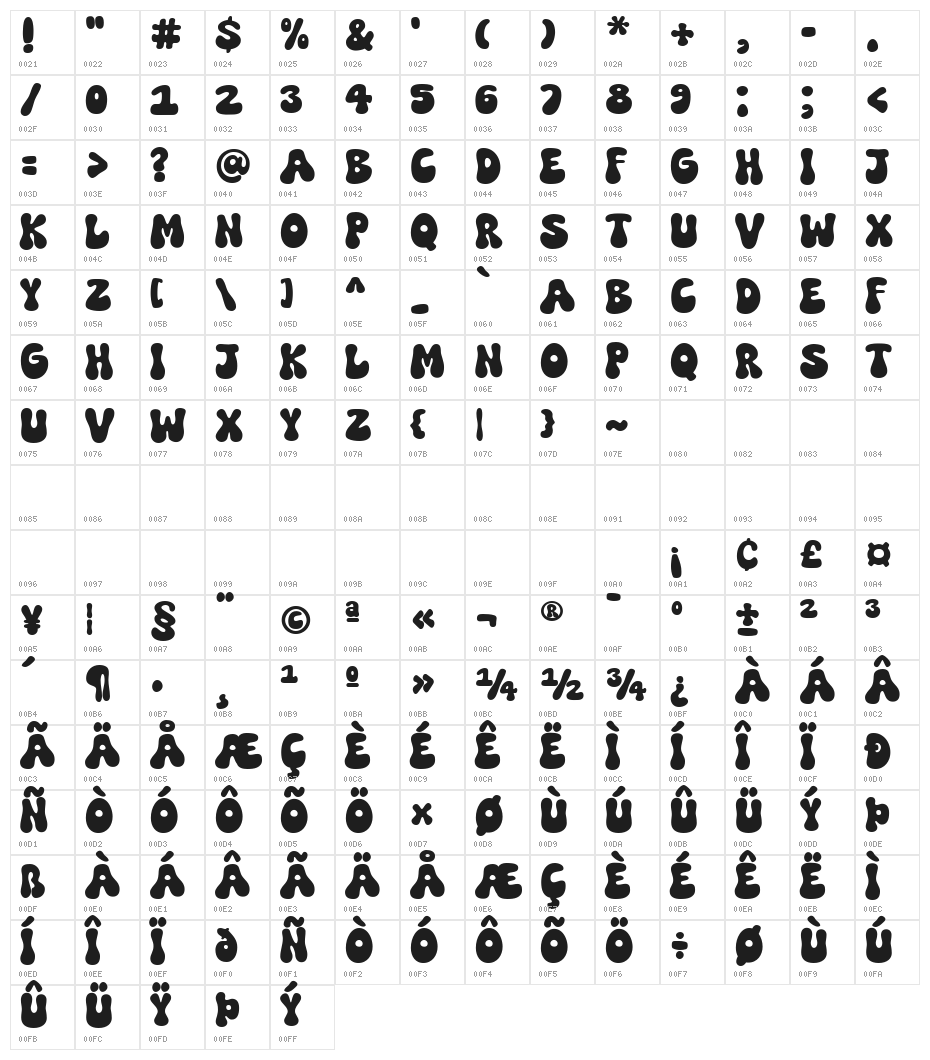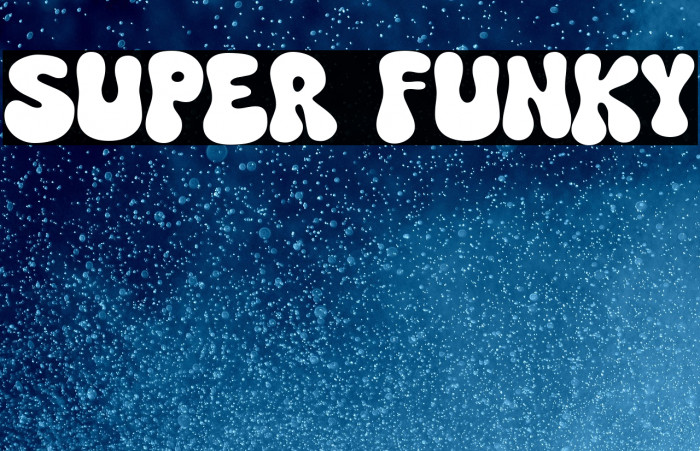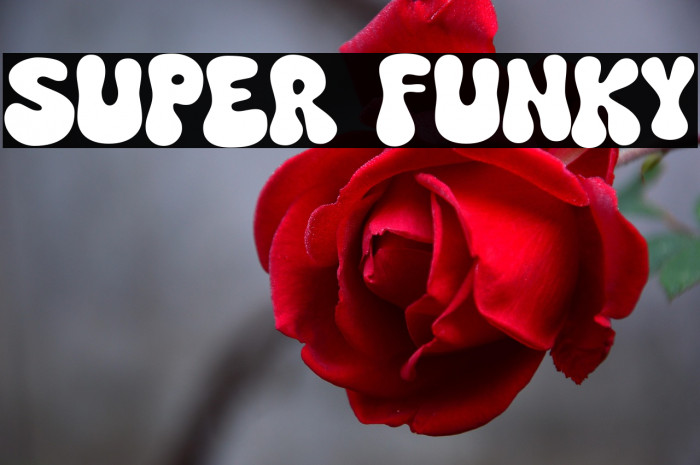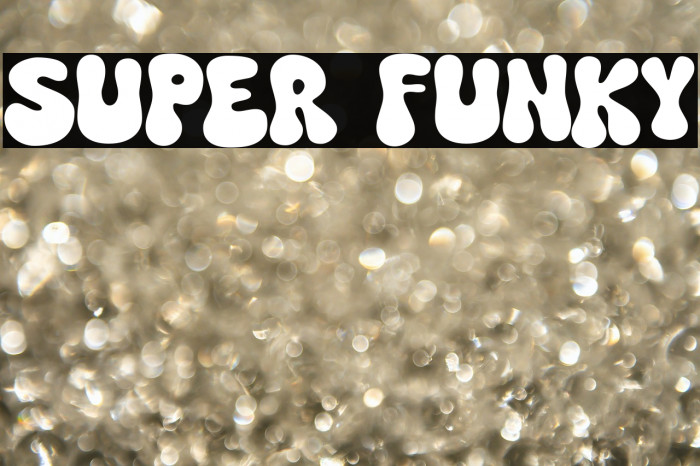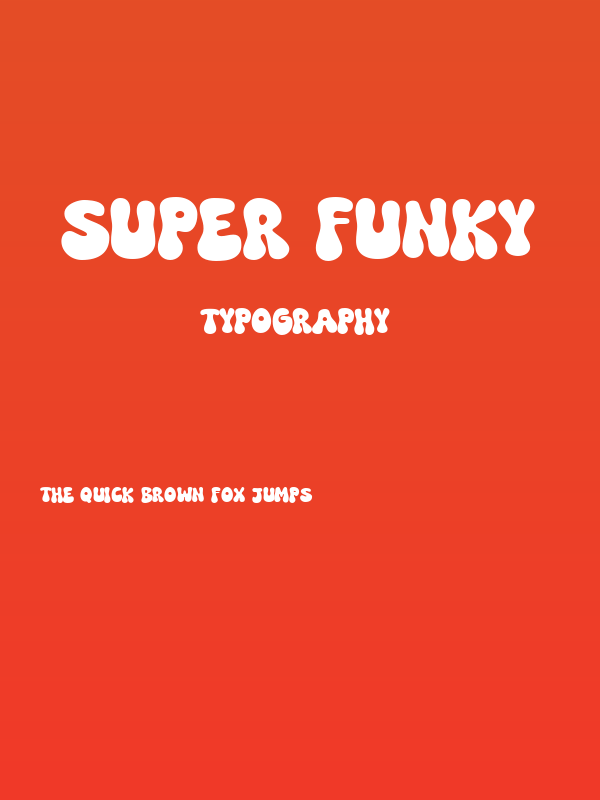
Super Funky Font
| Stile generale | Playful and Whimsical |
| Progetti proposti | Ideal for children's books, playful branding, party invitations, and creative posters. |